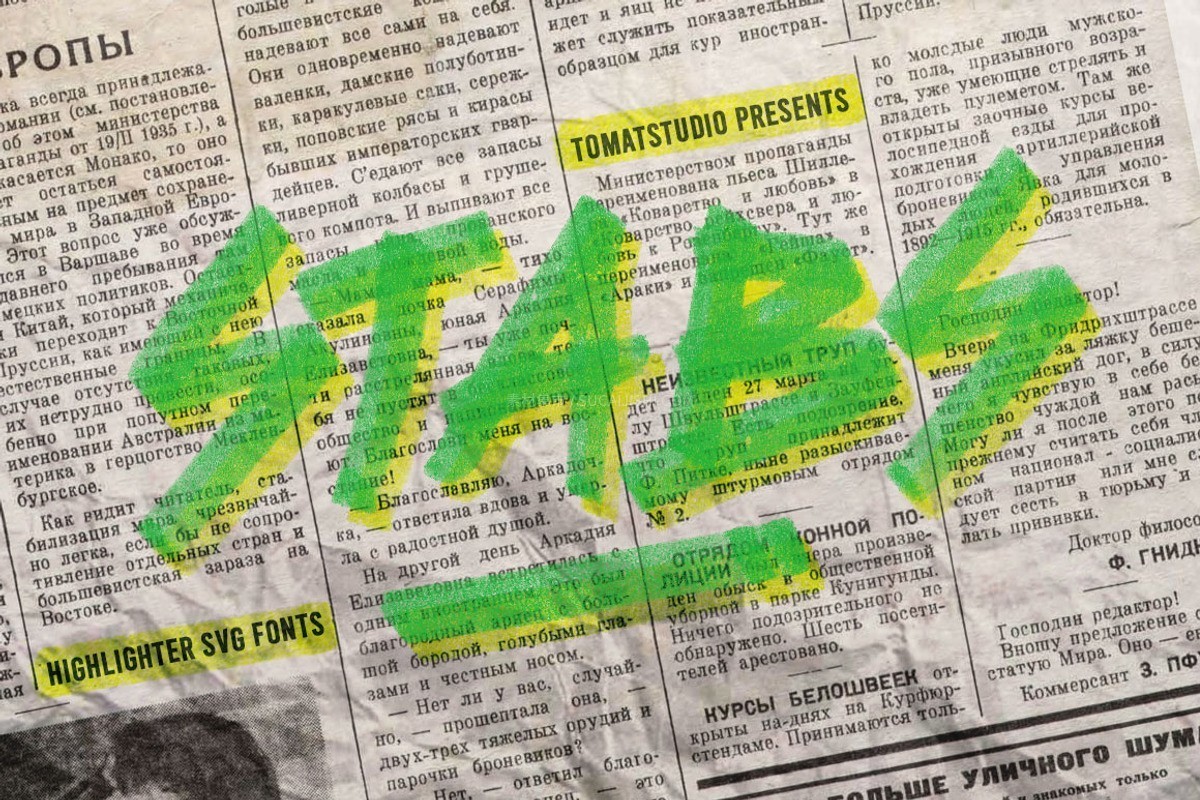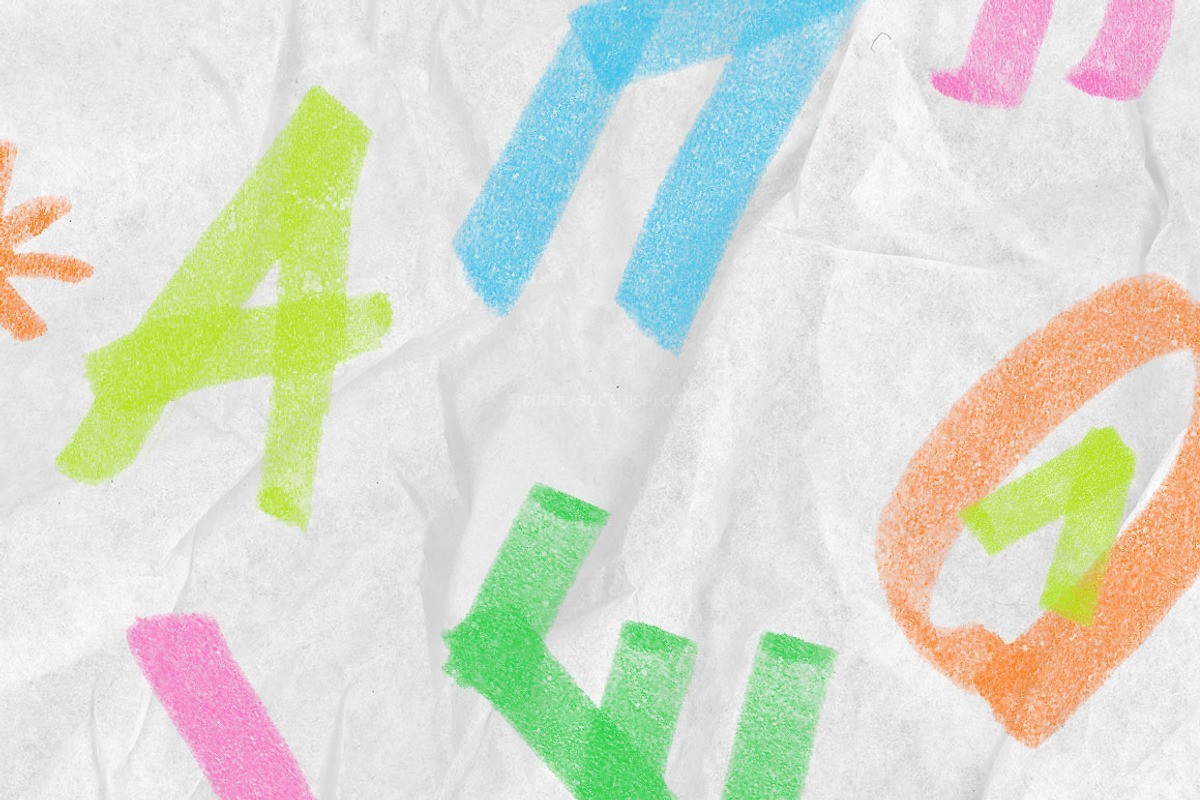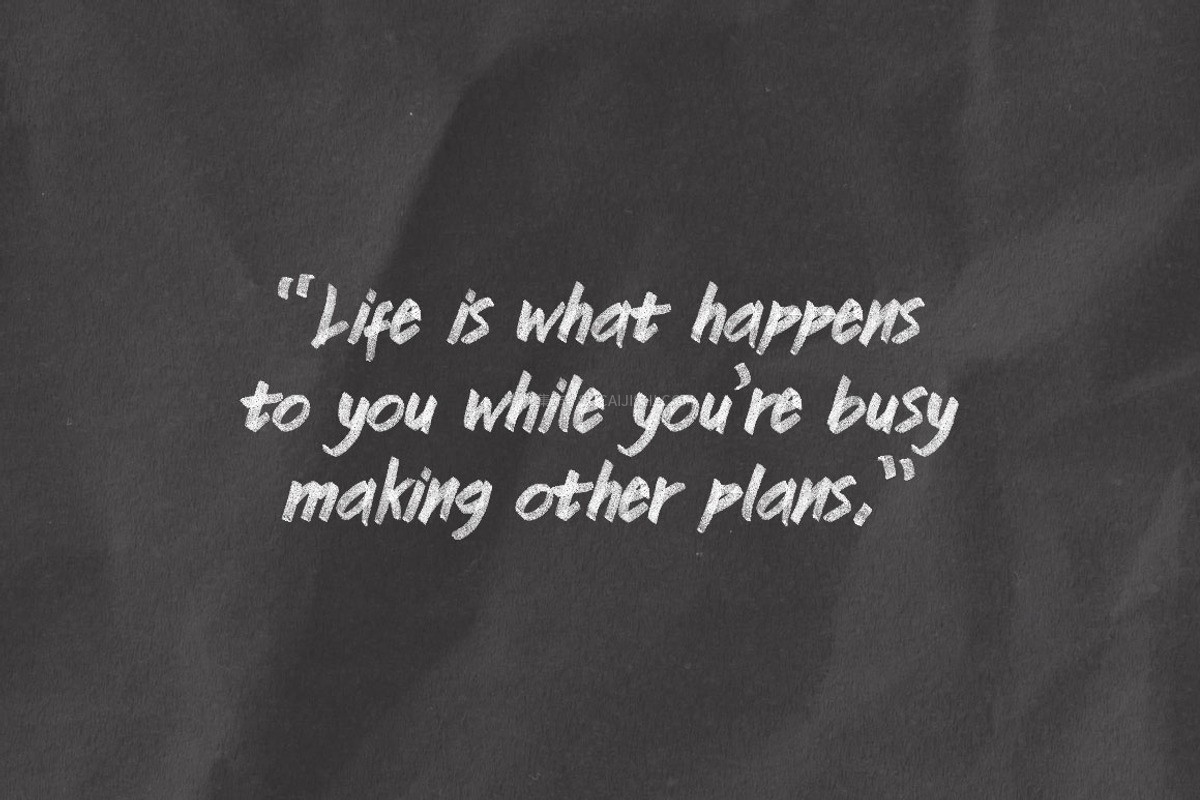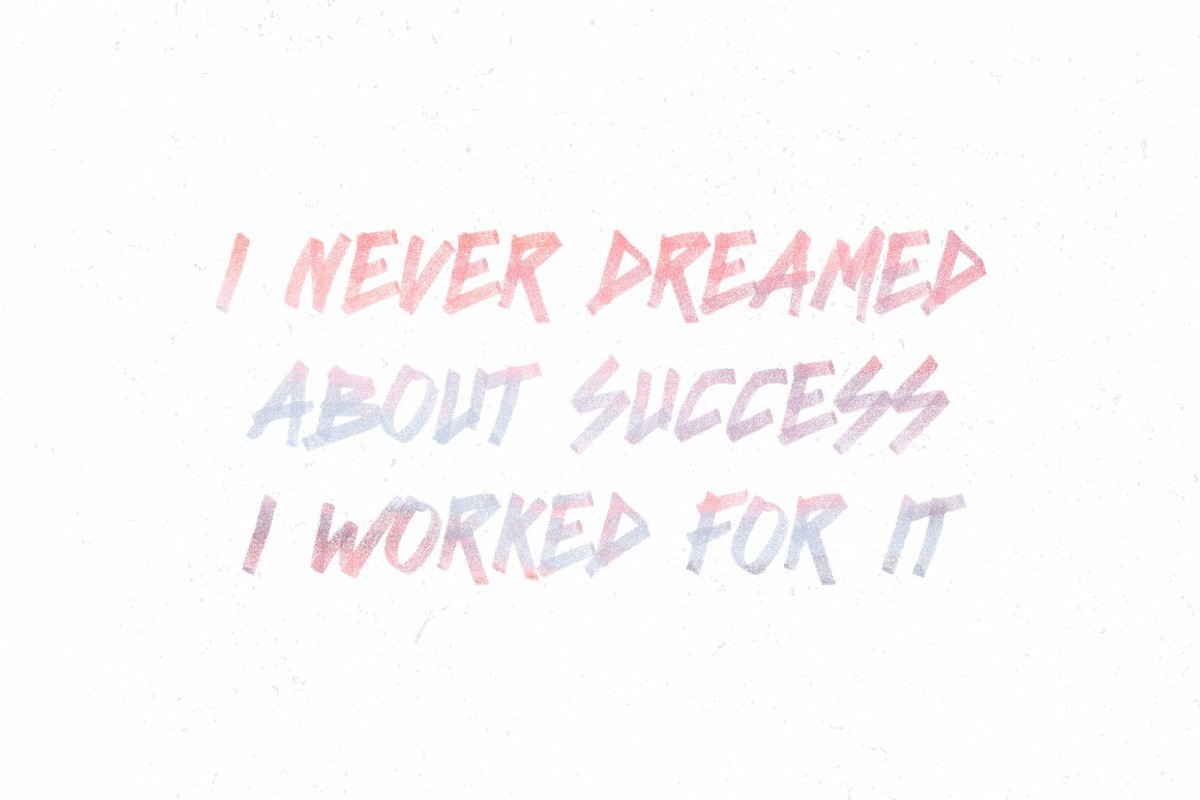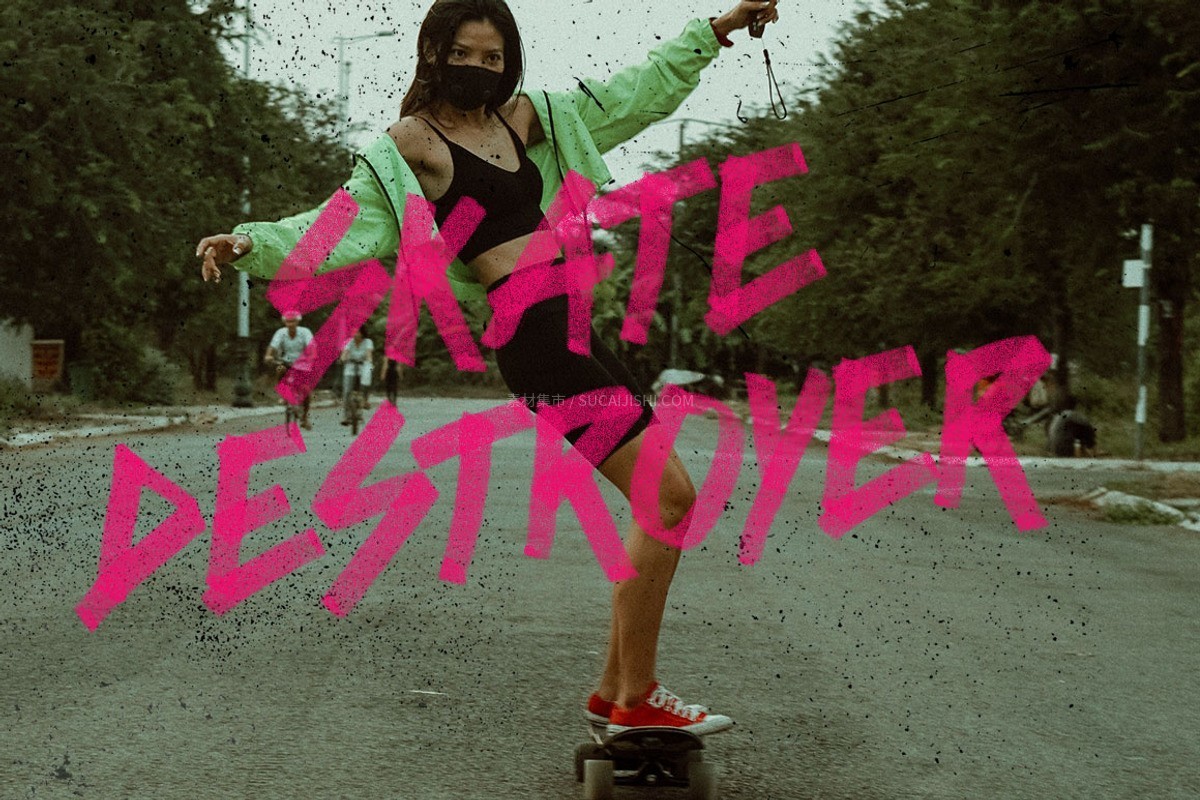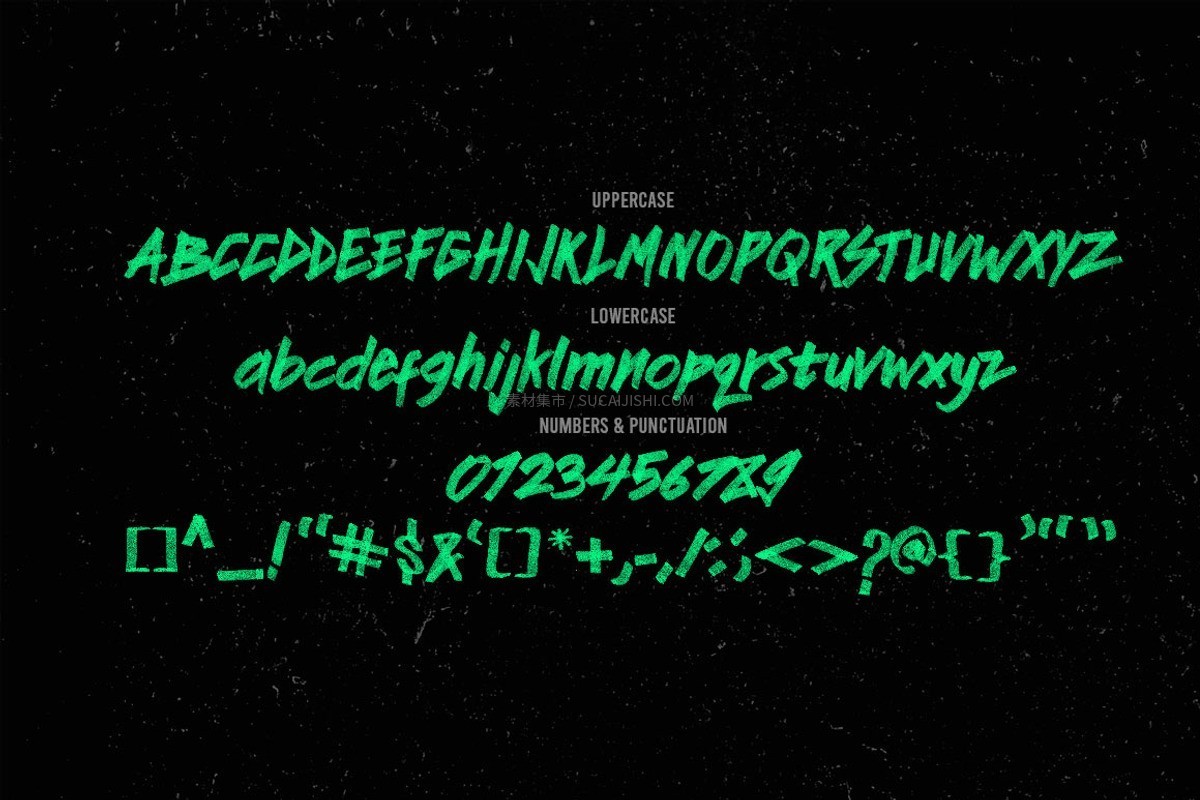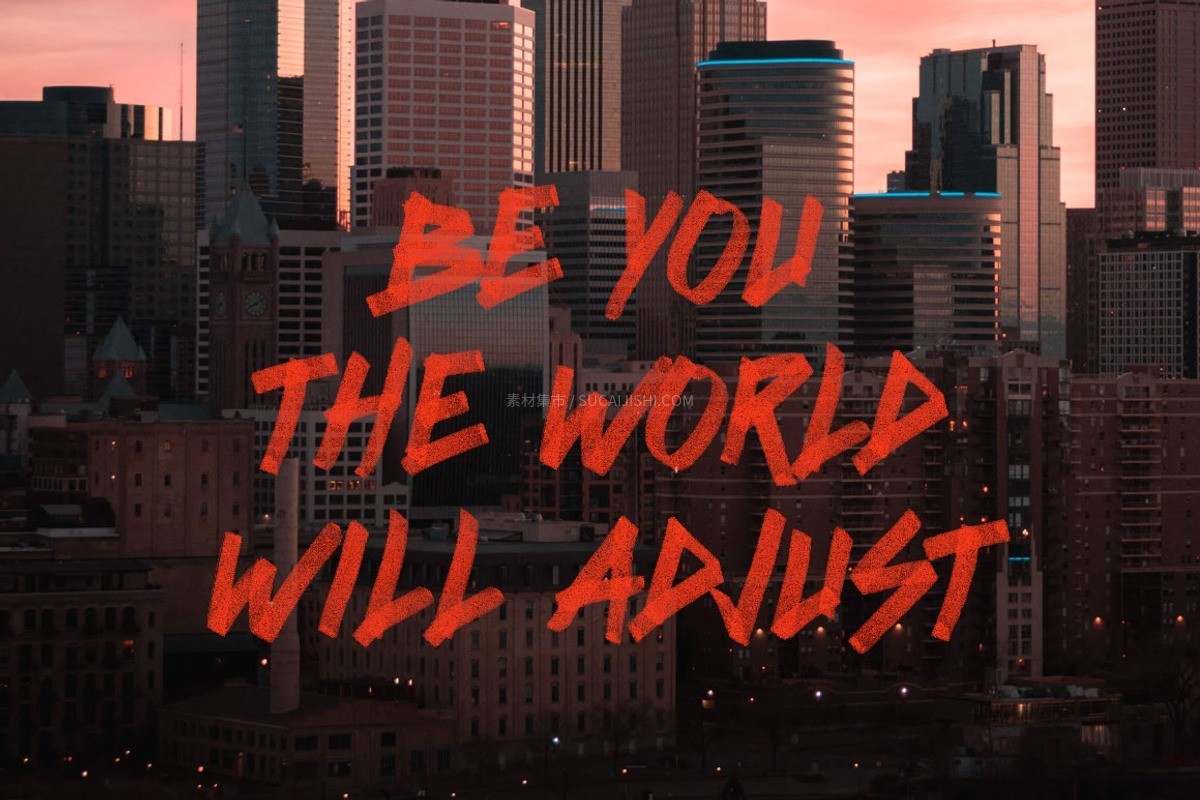
Stabs手绘荧光马克笔SVG字体
这款字体是用真正的荧光笔在图纸上一笔一画创作出来的,保留了超级逼真的手绘质感和透明的墨水纹理。它自带鲜艳夺目的高亮色彩,完美还原了只有 SVG 格式才能展现的通透效果(但也贴心地为你准备了常规字体格式)。非常适合用来给设计增加吸睛的亮点,更是打造 90 年代复古街头风的绝佳选择!